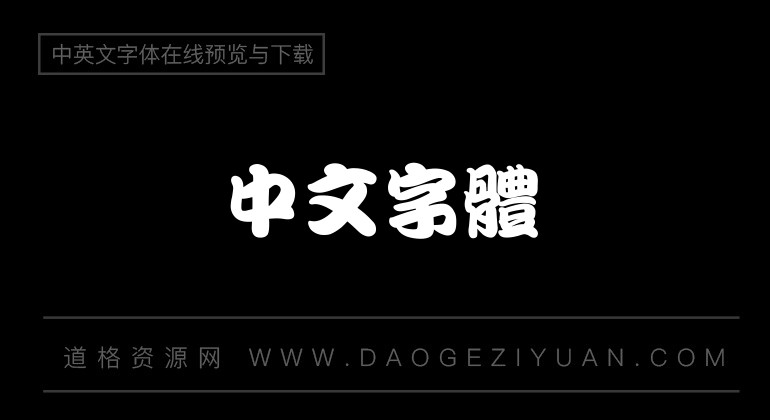
经典繁勘亭字体是一款源自于古典繁体文字的字体,由美国设计师陈青林设计,是一款精致的字体,具有古典繁体文字的独特魅力,有着清新的线条,拥有较高的可读性和较高的视觉效果,并且可以在多种语言环境下使用,是一款非常适合用于海报、书籍、网站和报纸等设计的字体。文件名:JingDianFanKanTing-1.ttf
经典繁勘亭是一款非常不错的手写艺术字体,具有很好的视觉感,适合于文化类的宣传设计、商业类品牌的广告和产品包装设计以及个性化文字排版等较多场景。